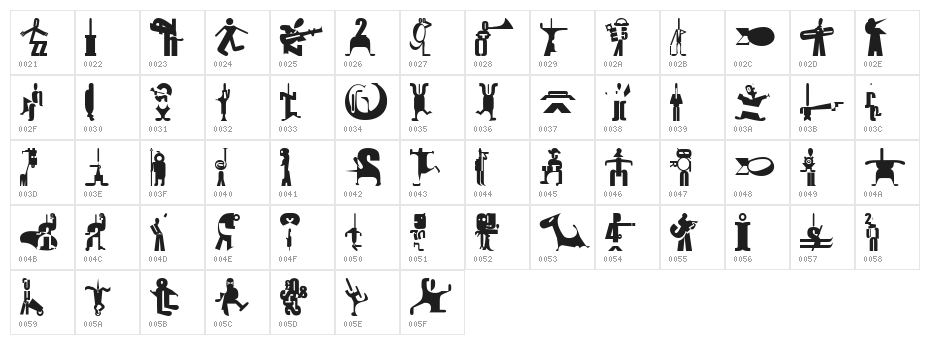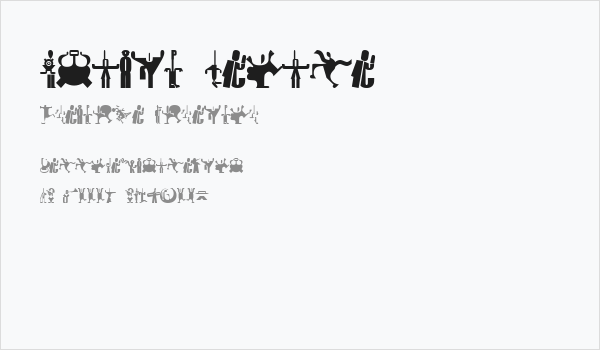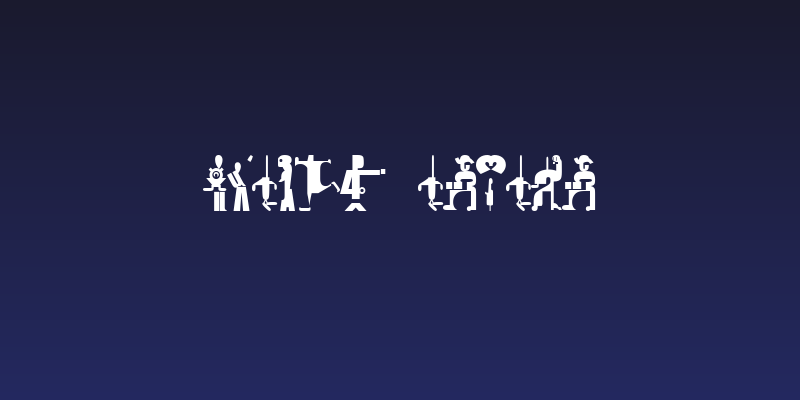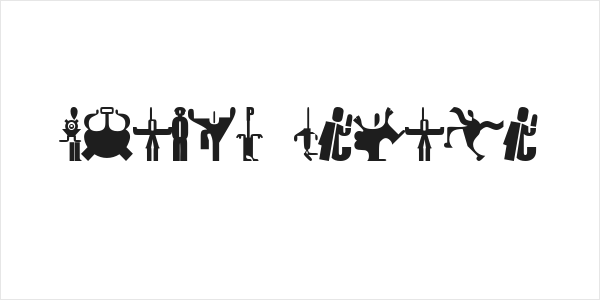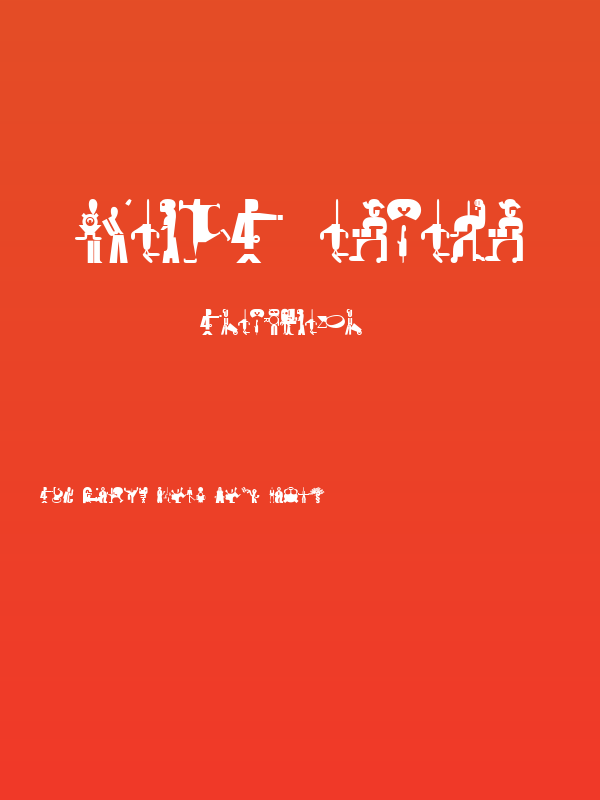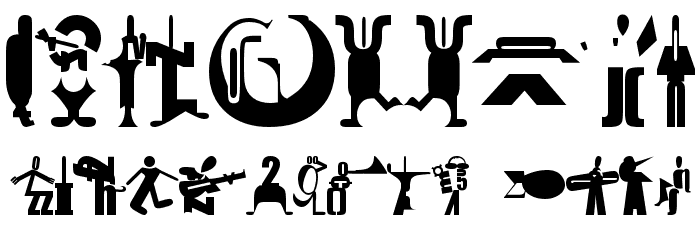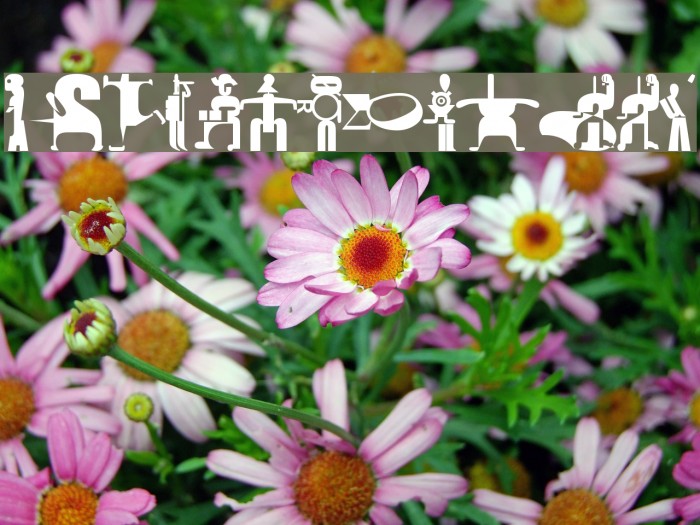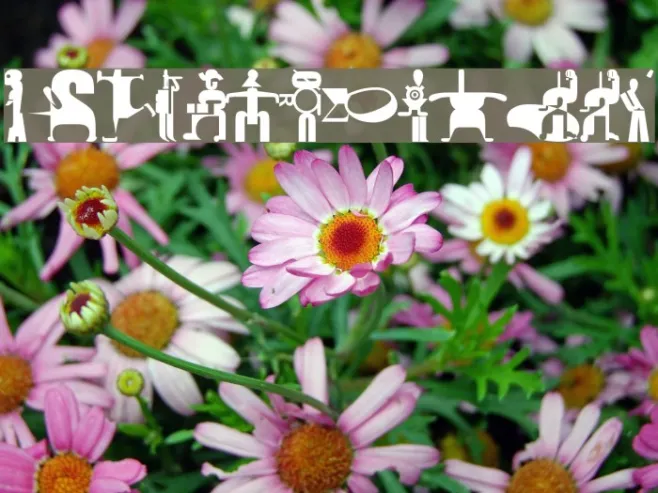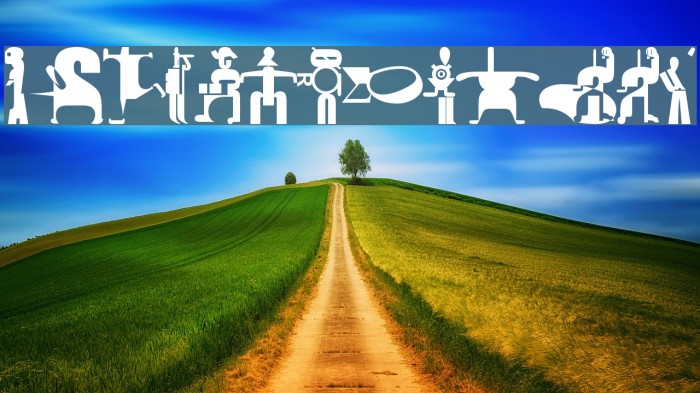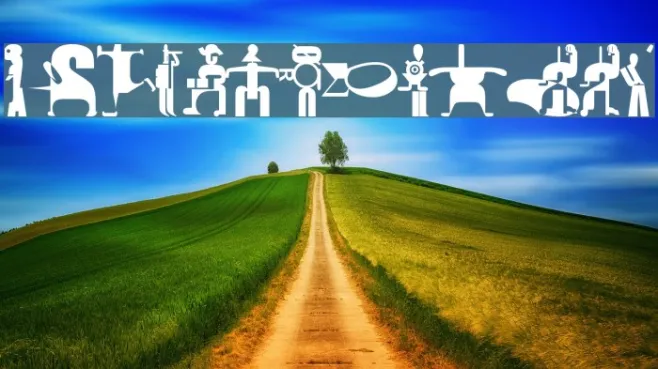
Impact People Font
| Caso d'uso | Logos, Posters, Artistic Designs |
| Progetti proposti | Ideal for artistic posters, creative branding, unique invitations, and any project that benefits from a playful and unconventional aesthetic. |